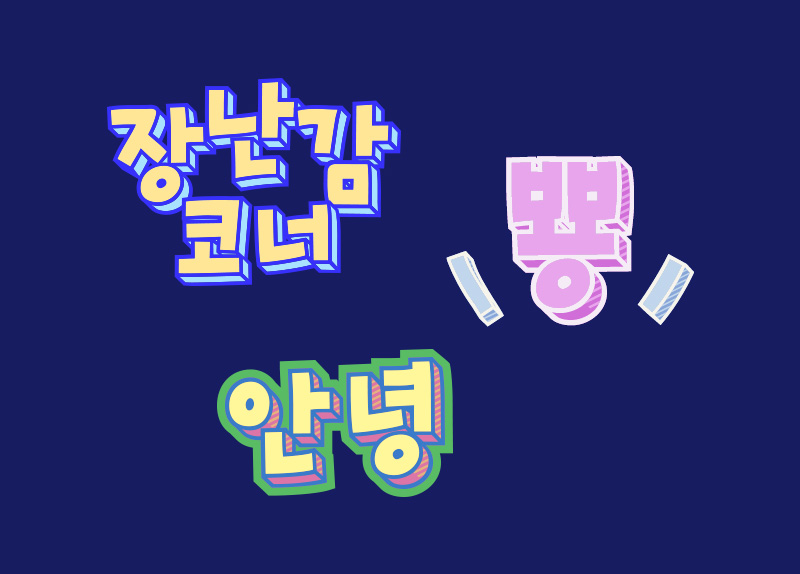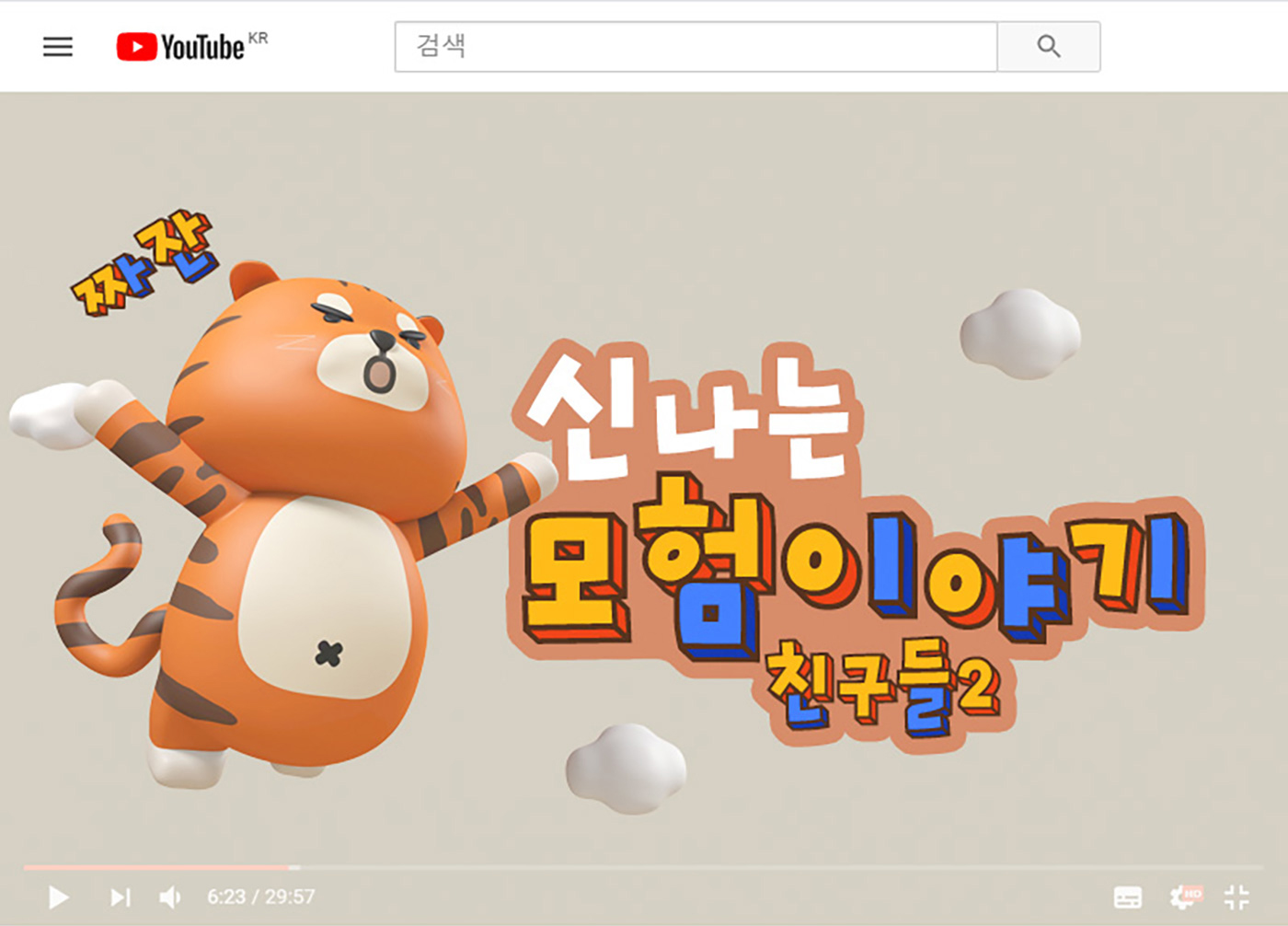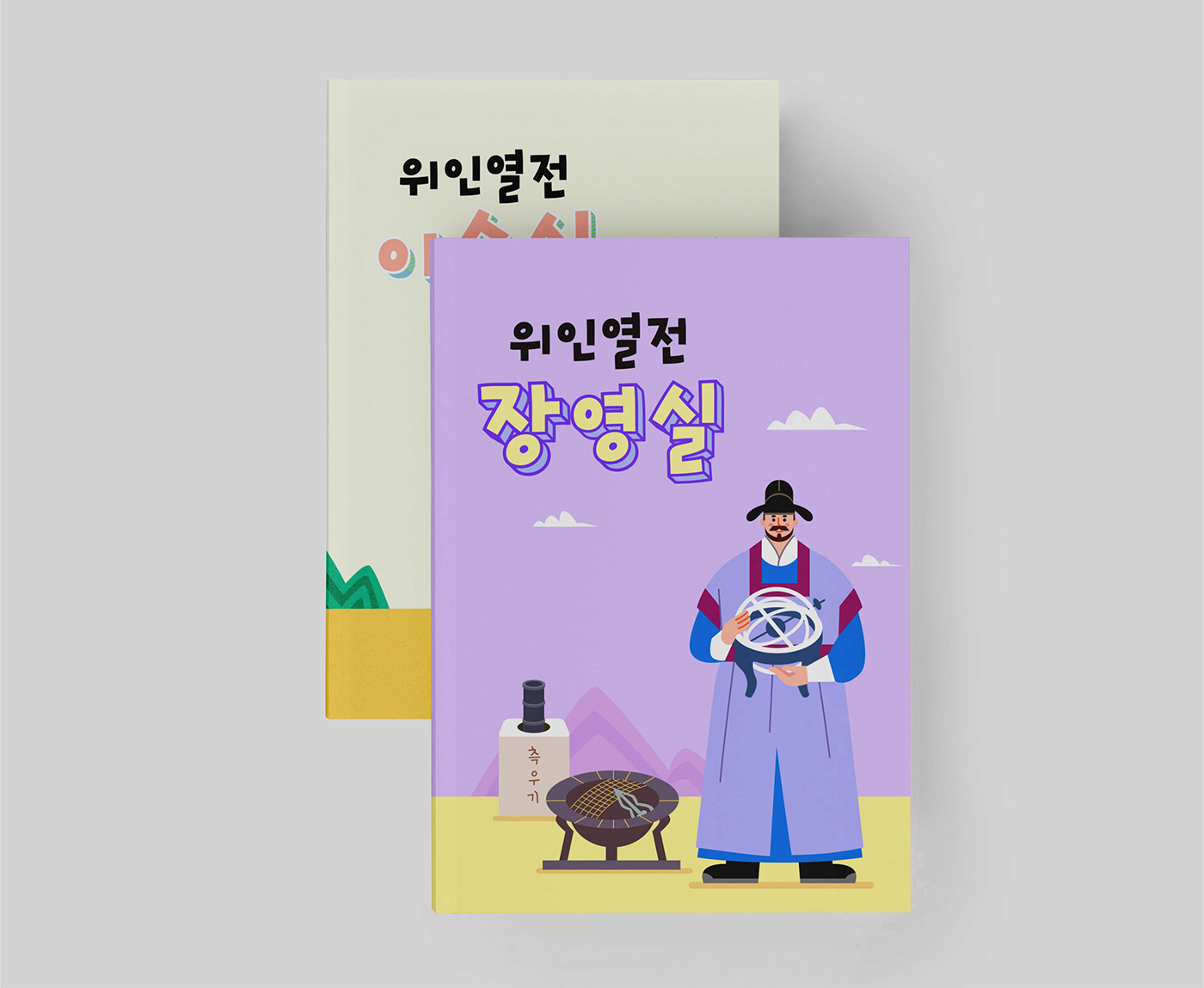
Rix토이컬러는 다채로운 색상과 재미있는 입체 효과들이 조합된 컬러폰트입니다.
발랄하고 귀여운 Rix토이스토리 시리즈의 글꼴로 별도의 수정 없이 컬러나 질감을 사용할 수 있습니다.
다양한 표현이 가능한 4가지 스타일과 그래픽 특징이 많아 타이틀, 자막 등에 활용하기 좋습니다.